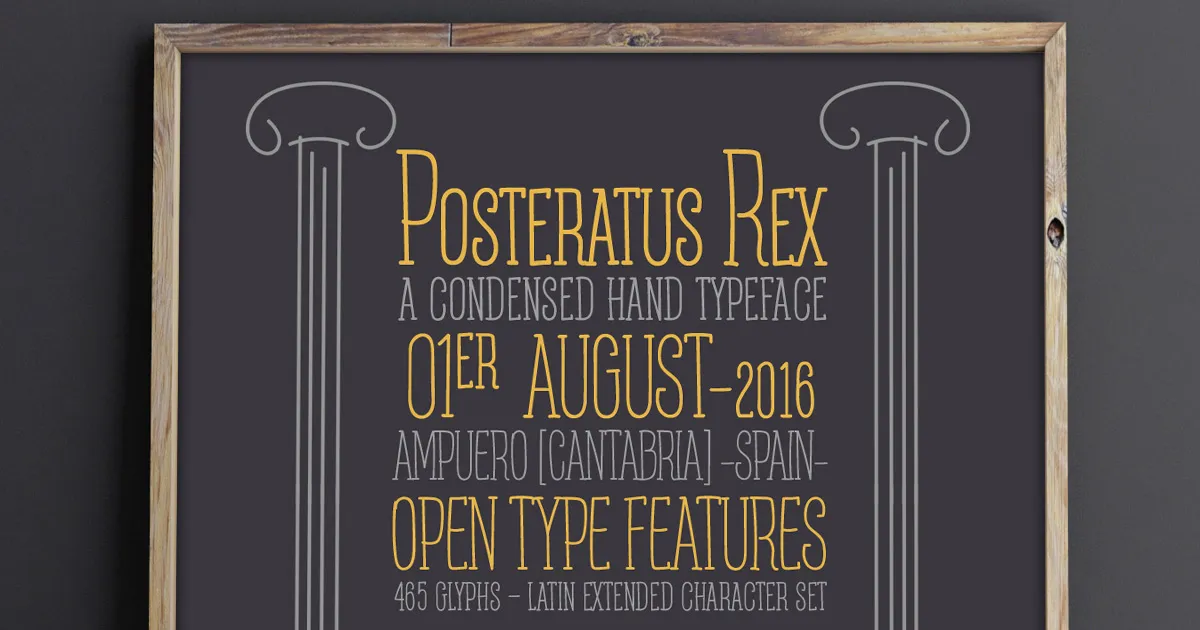
A Posteratus Rex é uma fonte handwritten que traz uma aparência elegante e concentrada, perfeitamente adequada para aplicativos exigentes como a criação de outdoors ou materiais de marketing digital. Com letras em caixa alta minúsculas e traços serifos em estilo de bastão finos, esta fonte oferece um contraste notável entre as letras maiusculas e minusculas, criando uma aparência vibrante e dinâmica. Suavizados ao menor tamanho, o design da Posteratus Rex faz dela uma escolha perfeita para layouts digitais altamente densos. Ela é a fonte ideal para textos de marketing digital ou outdoors onde cada palavra deve ser notada por sua relevância única, mas não exageradamente grande. Com seu conjunto de números também em caixa alta minúsculas, ela permite um design mais consistente e coerente. Esta fonte handwritten, com suas linhas elegantes e contrastes pronunciados, é uma ótima escolha para designers que buscam criar um impacto visual forte e único. Composta por um designer talentoso chamado defharo, a Posteratus Rex oferece um contraste sofisticado em uma paleta de escrita handwritten perfeita para ambientes digitais exigentes.